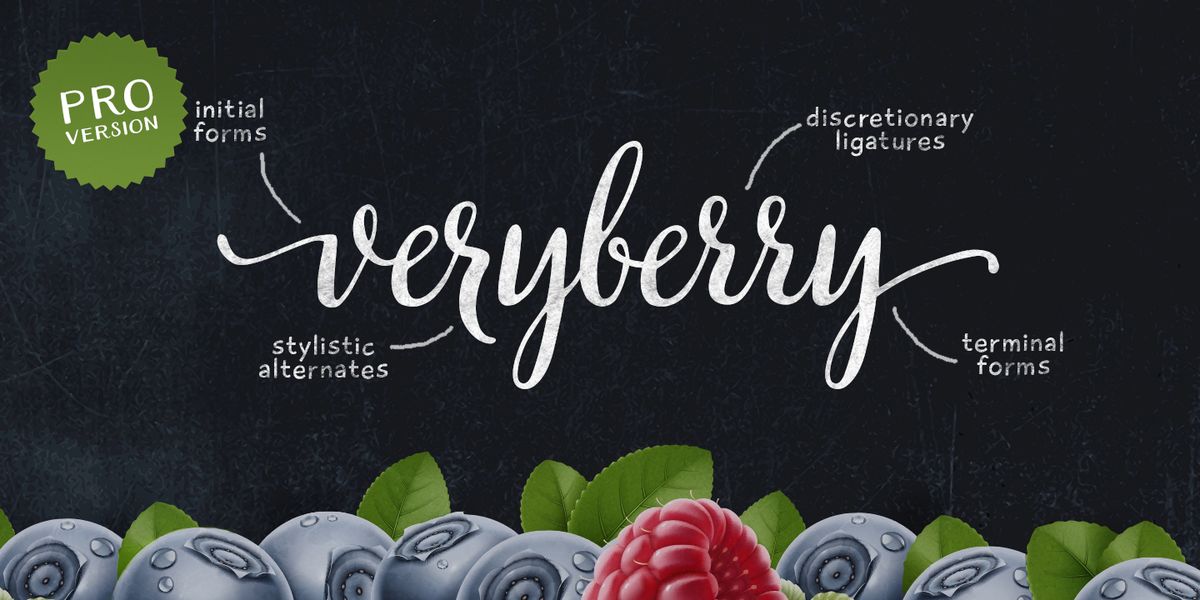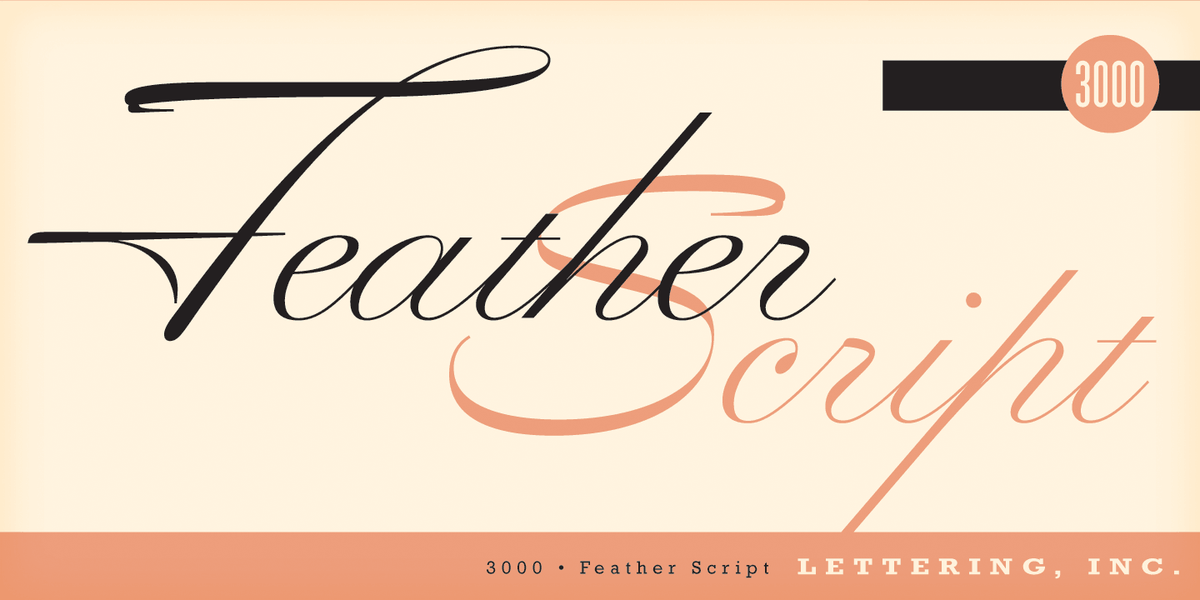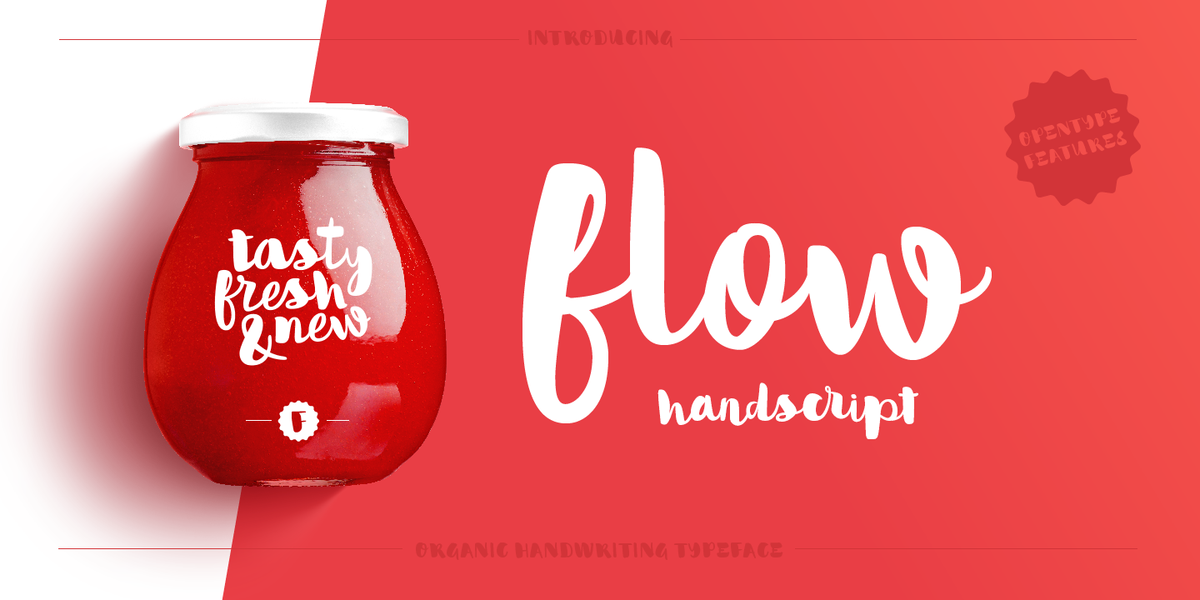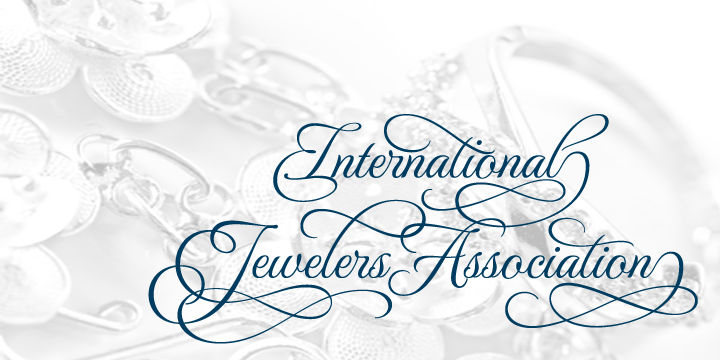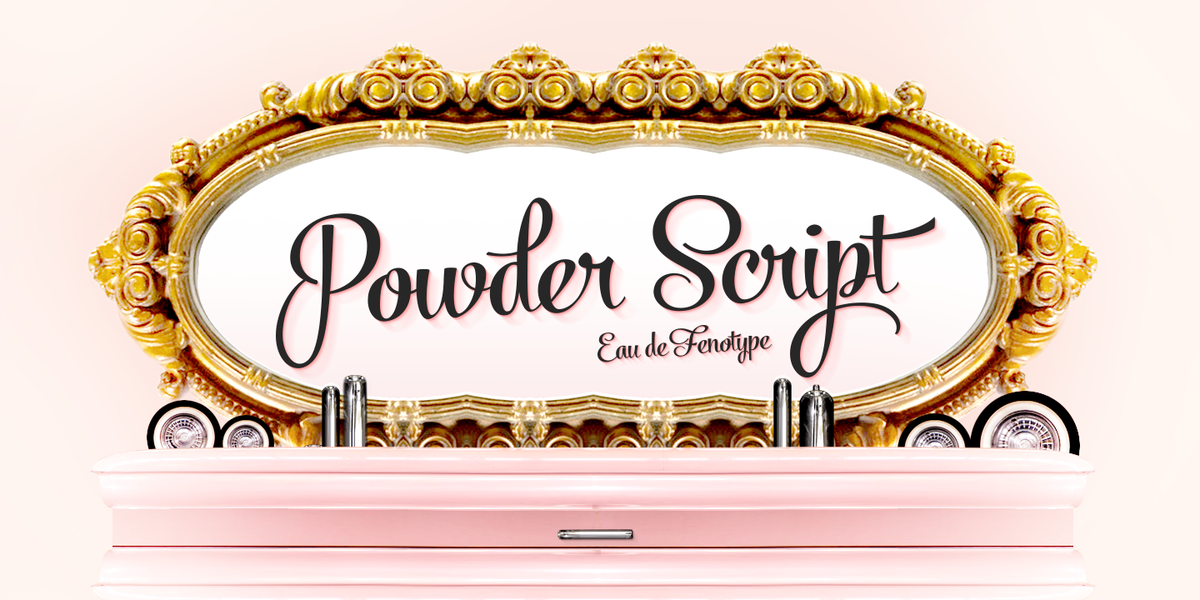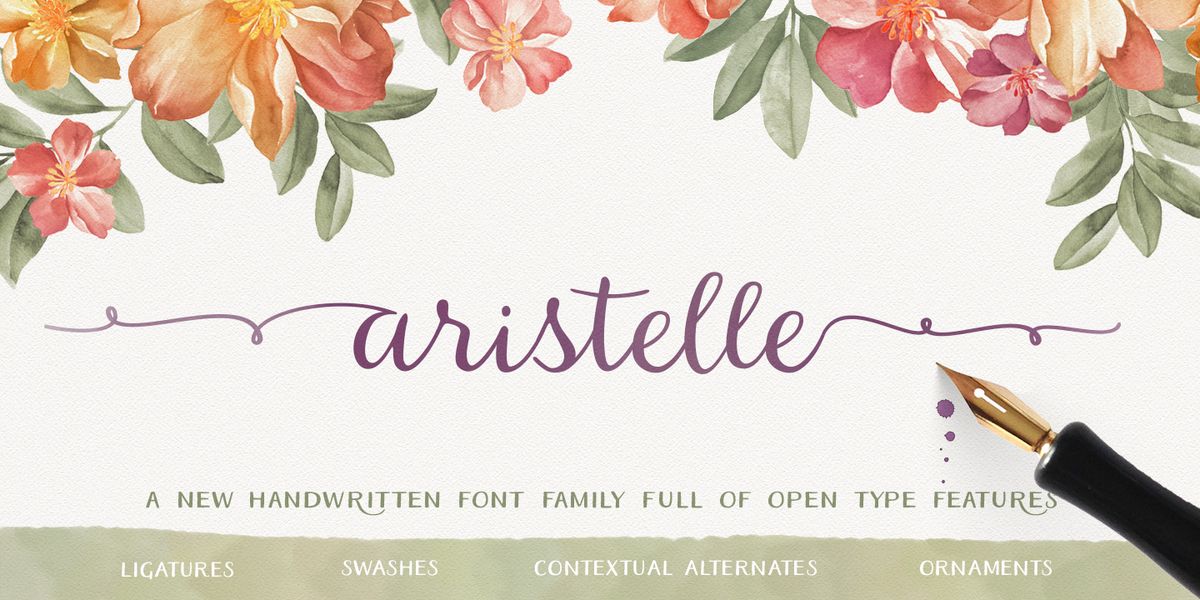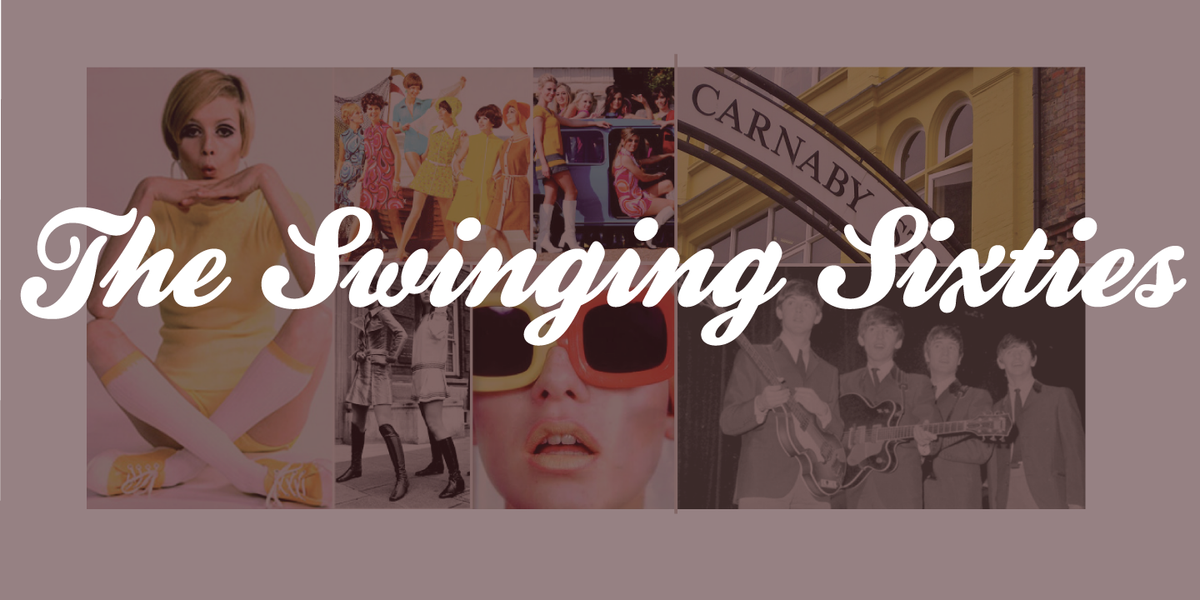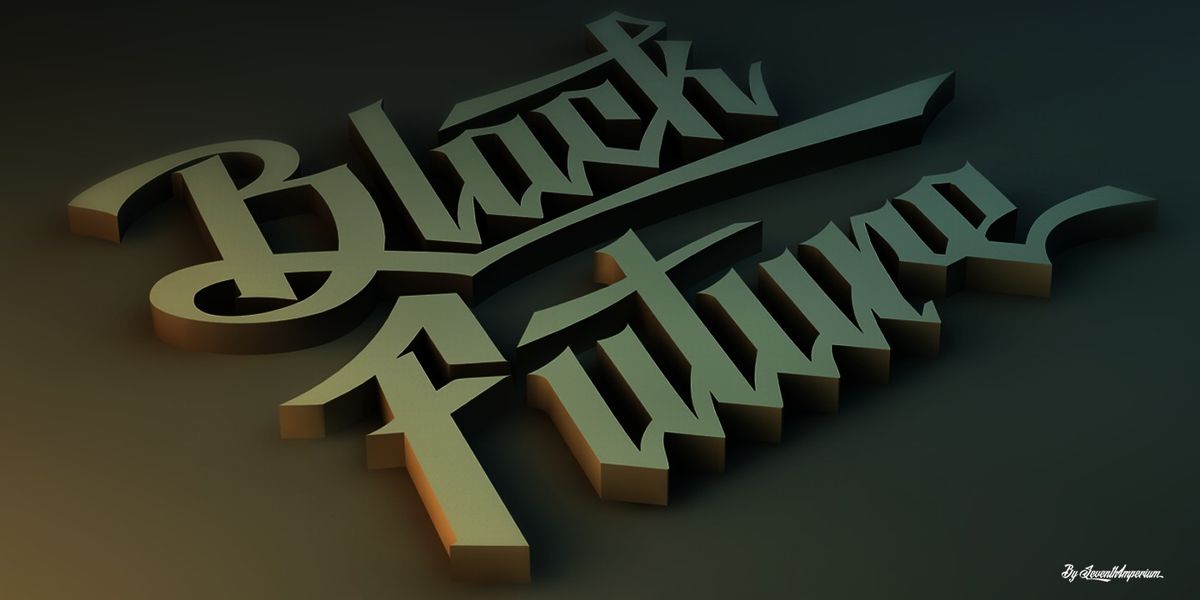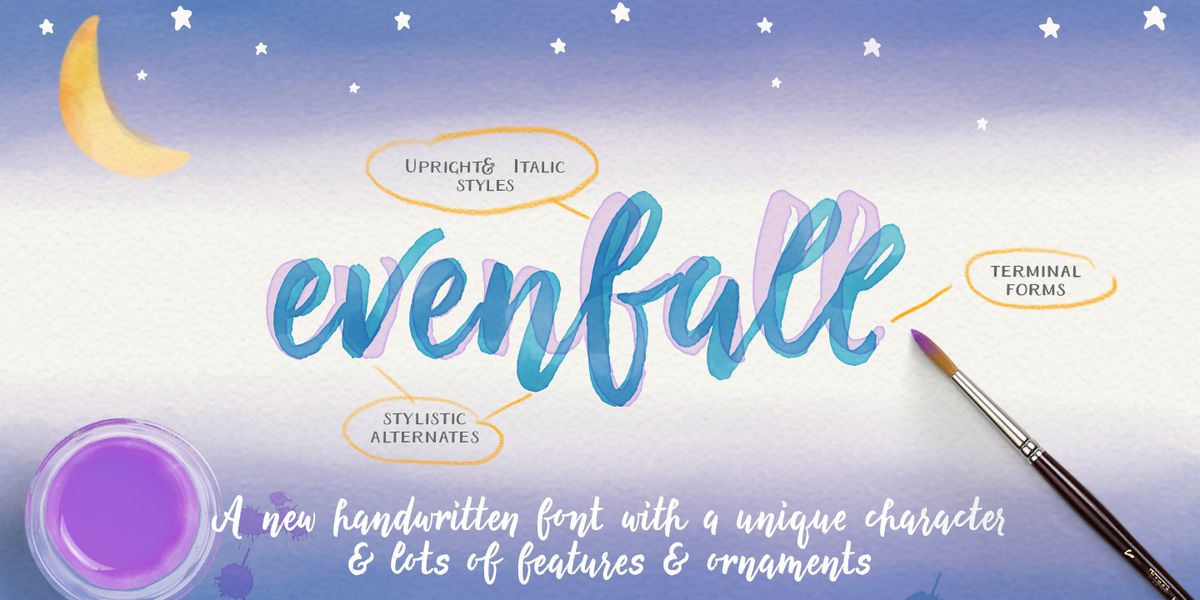
25 fuentes de caligrafía imprescindibles para tus diseños
Una gran parte de cualquier diseño es el texto que lo acompaña. No importa cuán cautivadoras sean sus imágenes, sin la elección de fuente correcta para complementarlas, el producto final siempre carecería del ingrediente que necesita para seducir por completo a la audiencia.
El antiguo arte de la caligrafía
Aquí es donde entra la belleza de la caligrafía. La caligrafía es más que solo escribir. Es el antiguo arte de hacer que sus letras y números habituales sean un poco más interesantes de lo que normalmente aparecen, haciéndolos más expresivos y dándoles un flujo más fascinante.
Los calígrafos pueden usar bolígrafos o pinceles, según lo que más se adapte a su estilo. Y aunque los calígrafos clásicos pueden desviarse de las estrictas reglas de tipografía que dicta la tipografía moderna, los artistas modernos a menudo encuentran que mezclar ambos enfoques casi siempre termina con un resultado final aún mejor.
Existen diferentes estilos y enfoques de la caligrafía, dependiendo de la influencia. La caligrafía europea, por ejemplo, ilumina la primera letra de una página, un capítulo o un párrafo de la misma manera que se usa la letra mayúscula en el diseño moderno.
Los tamaños y el estilo de los personajes también pueden diferir, lo que da como resultado un atractivo más resistente y hecho a mano. Los estilos del este asiático, de la misma manera, se desvían de los estándares estrictos para darle más espíritu a cada trazo.
El enfoque moderno
Poner la caligrafía tradicional y la caligrafía moderna una al lado de la otra mostraría una serie de diferencias, pero definitivamente también surgirá una larga lista de similitudes.
Esto demuestra que, aunque los calígrafos modernos han encontrado nuevos enfoques que les funcionan mejor con el uso de las herramientas modernas de hoy, todavía hay mucha sabiduría que extraer de las obras de los artistas originales.
Donde la tipografía ahora juega un papel importante en cualquier diseño, la caligrafía es una de las mejores formas de hacer las cosas aún más interesantes. Después de todo, hay algo un poco más personal cuando se usa la caligrafía, la razón principal por la que se la prefiere sobre otros diseños y enfoques de fuentes más mesurados.
Aquí hay 25 fuentes de caligrafía diferentes que podrían funcionar bien con los diseños en los que está trabajando actualmente. Estas fuentes capturan las razones exactas por las que la gente prefiere la caligrafía a cualquier otra cosa, lo que demuestra que, aunque la caligrafía ha existido durante siglos, no es algo de lo que nos despediremos en un futuro próximo.
1. Mulberry Script de Cultivated Mind
Mulberry es un hermoso guión de caligrafía manuscrita que viene con encantadores suplentes, ligaduras, extras y adornos. Elija entre Mulberry Script o Mulberry Script Pro y dos pesos de fuente (Regular / Negrita).
Mulberry Script viene con un conjunto básico de alternativas. Mulberry Script Pro viene con cuatro conjuntos de alternativas, incluidas las ligaduras. Este tipo de letra se puede utilizar para moda, indumentaria, papelería, revistas, tipografía, películas, libros y marketing.
2. Boho por latinotipo
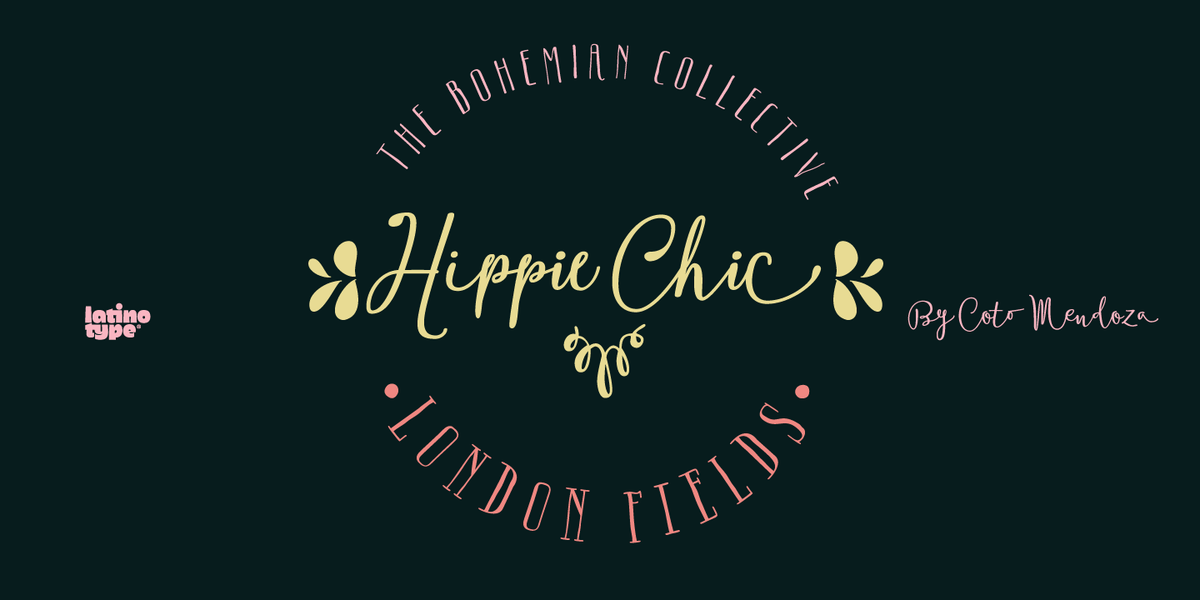
Boho está inspirado en una chica bohemia que es un alma libre y un espíritu creativo. Es una chica de ciudad, pero le encanta pasar mucho tiempo al aire libre y estar cerca de la naturaleza. Le encanta el arte e ir a los mercados de antigüedades y alimentos orgánicos.
Ella es un espíritu libre y salvaje que no conoce límites. Boho consta de 4 subfamilias: Script, Line, Sans y Serif. Cada subfamilia viene en 4 pesos: Regular, Negrita, Cursiva y Negrita Cursiva.
Las versiones Script y Line incluyen una variante de terminal en forma de lágrima. También se incluyen dingbats y adornos.
3. Drina de Posterizer KG
Drina es un guion fuente manuscrita con un look casual y moderno. Debido a la espontaneidad, hay muchas ligaduras estándar y discrecionales para evitar la repetición frecuente de letras.
Nota: Las imágenes de vista previa se ven terribles, pero la fuente es hermosa.
MonteCarlo es un hermoso guión formal, tanto contemporáneo como tradicional. La cursiva de este guión de conexión es leve, lo que lo convierte en un diseño extremadamente legible.
Sus opciones florecientes adicionales ofrecen posibilidades verdaderamente diversas para la personalización de la pantalla. MonteCarlo es perfecto para aquellas situaciones que requieren una apariencia ornamentada y un mensaje legible, sin comprometer el hermoso diseño.